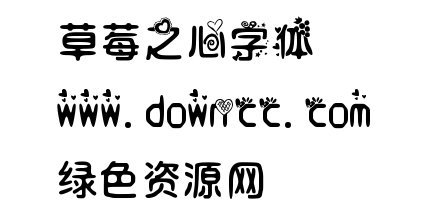
草莓之心字体与草莓恋人字体的风格比较相似,都是偏于卡通q萌的pop字体,字里行间充满了各种心形图案,或实心、或空心等,活泼动人,很能吸引读者的眼光,绿色资源网诚意推荐!
草莓之心字体新浪微博po主暖色君的作品,是在原华康华综变字体上美化而来,增加了丰富的卡通图案,心形、草莓性、兔耳朵形状等,非常有创意。
草莓之心是一款带心的可爱字体,很能满足广大朋友的少女心和童心,给文字增加独特的装饰,更加醒目,可以使用在关于儿童童话、恋爱情侣之间的情意表达,给你的平面设计增添独特魅力。